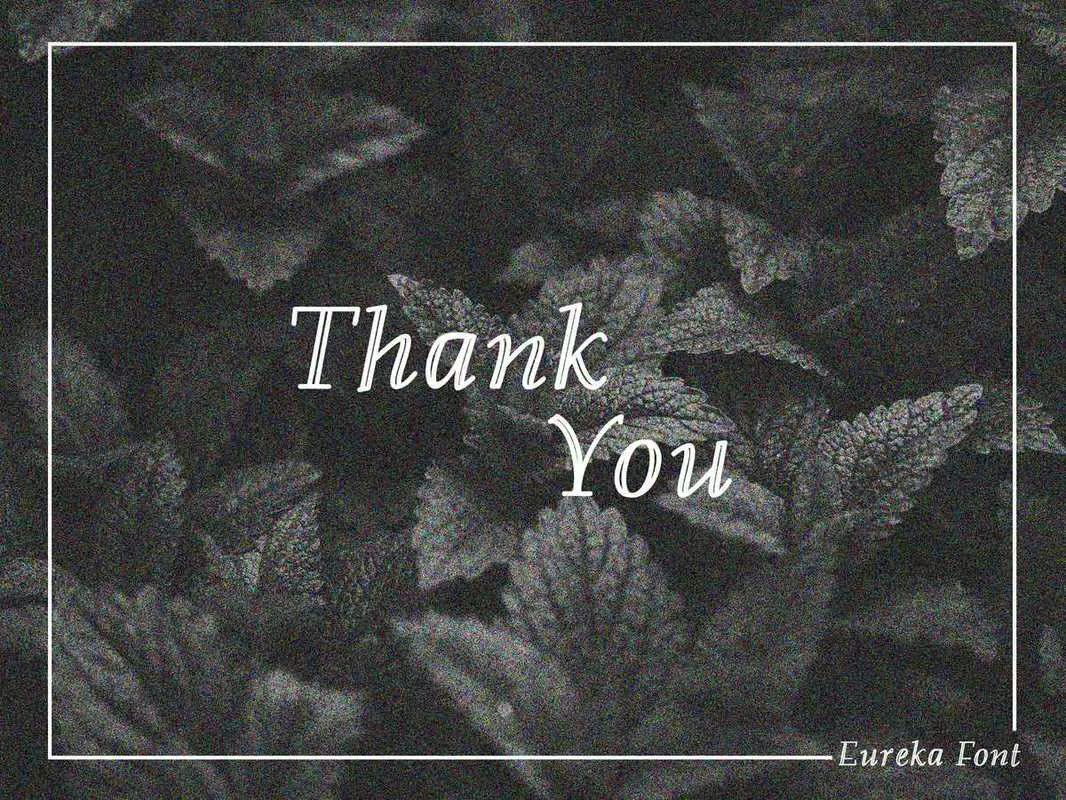
Eurekais优雅时尚的桌面。Eurekais完美的产品包装、品牌项目、产品设计、徽标、标签、邀请函、社交媒体、广告、照片和需要手写的项目品味。享受内容并自由反馈。发送电子邮件。如果您喜欢此字体,请访问和查看。谢谢^^ Eurekais优雅时尚的桌面。Eurekais完美的产品包装、品牌项目、产品设计、徽标、标签、邀请函、社交媒体、广告、照片和需要手写品味的项目。享受内容并自由反馈。发送邮件。如果您喜欢此字体,请访问和查看。谢谢^^